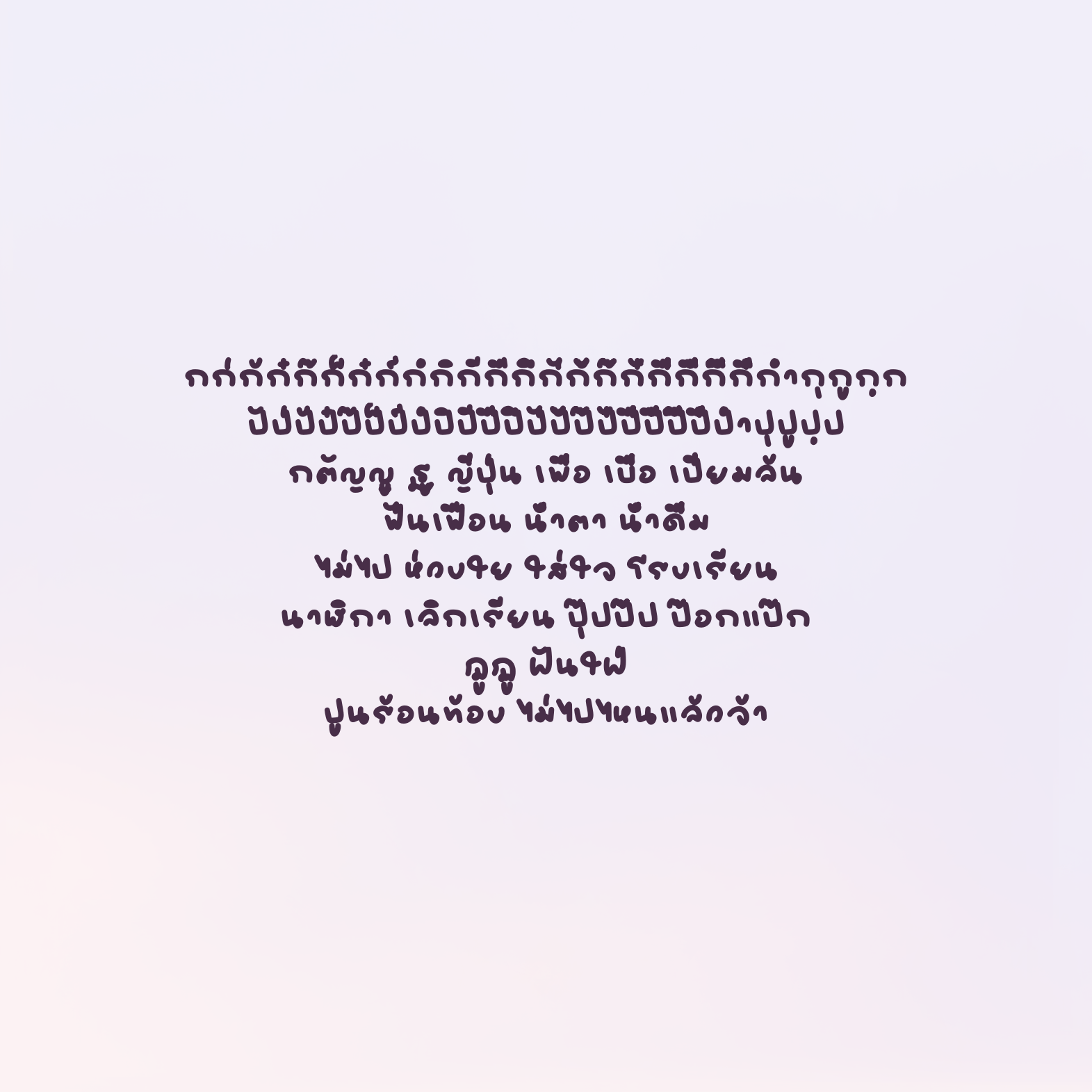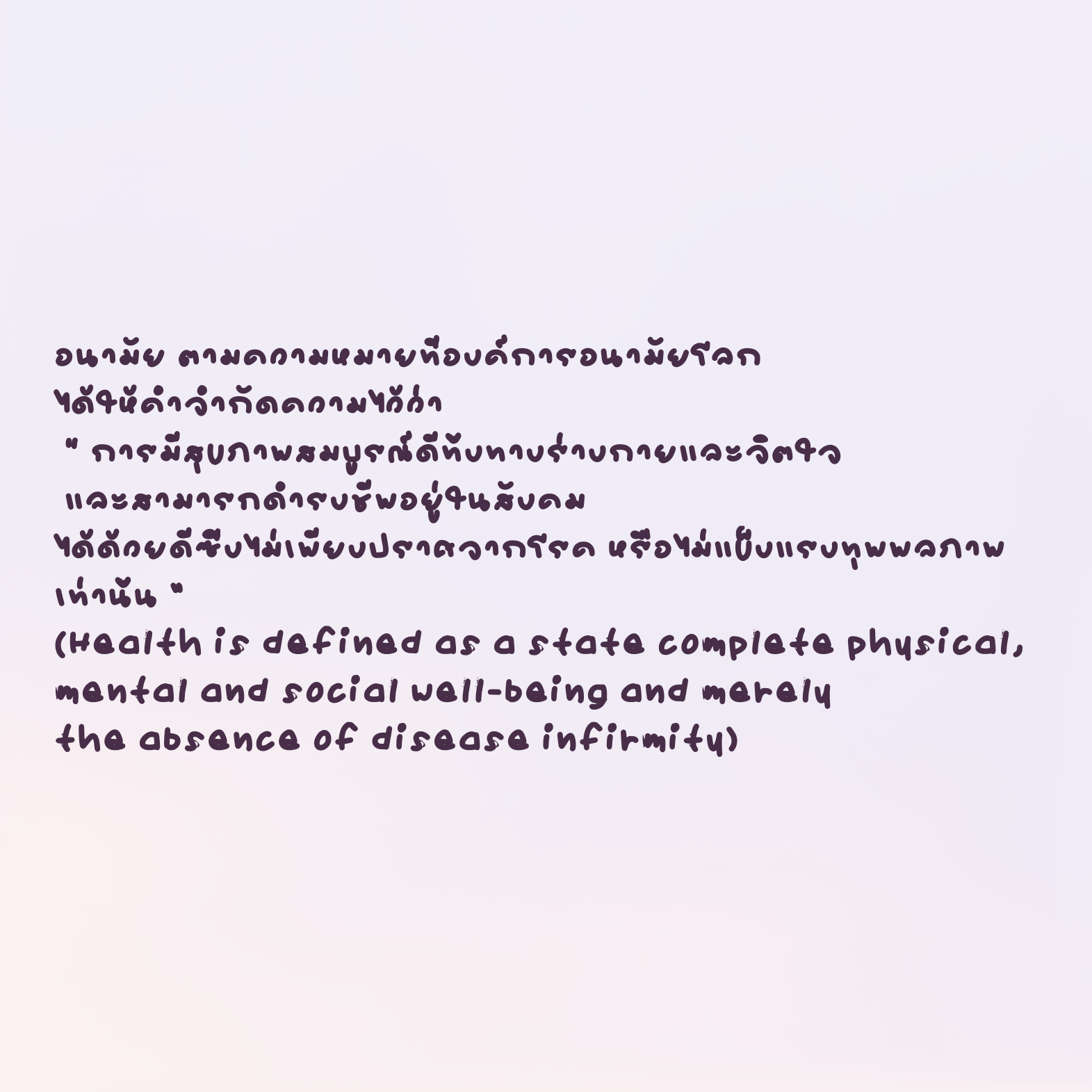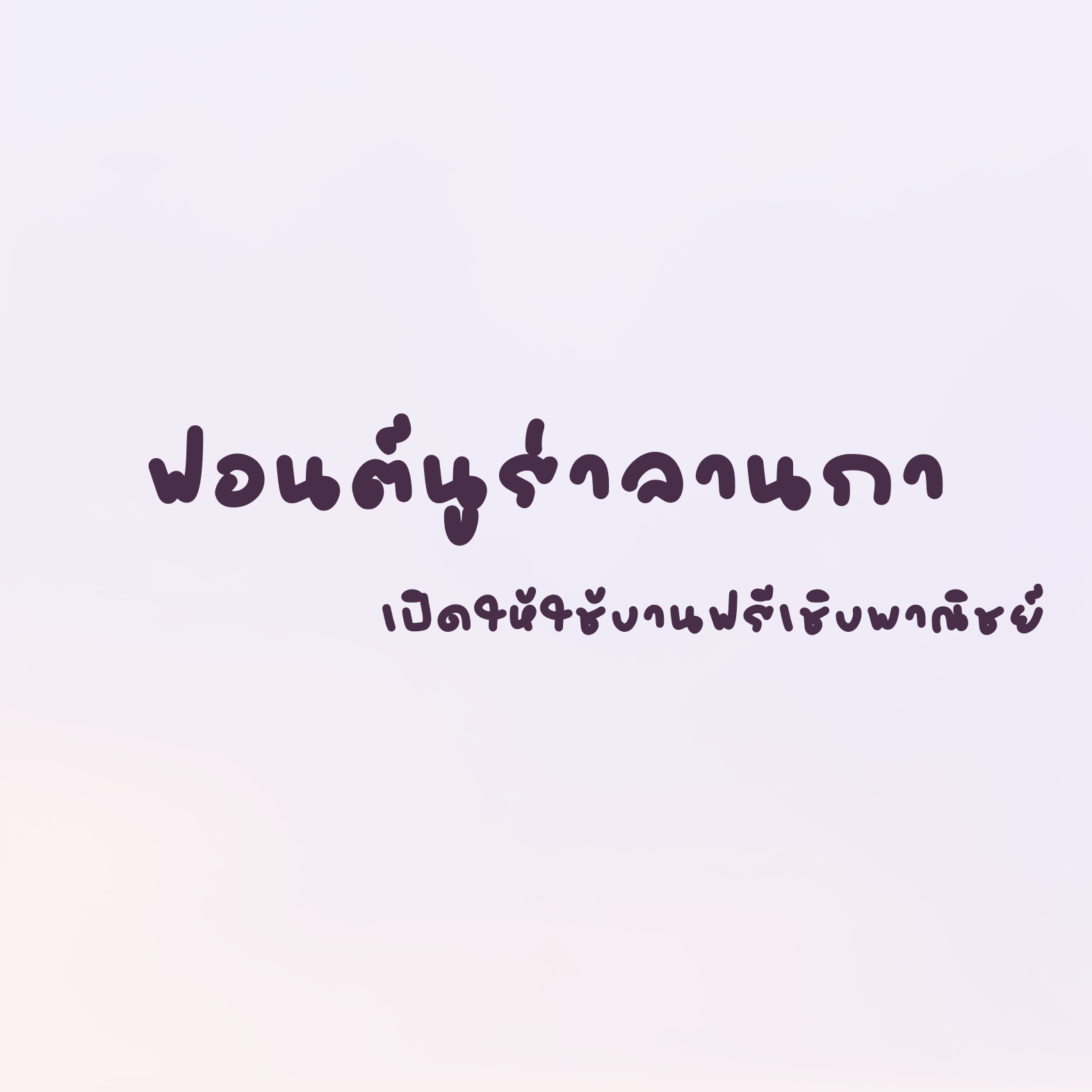
นูร่าลานกา (Nura lanka)
ฟอนต์ลายมือ  ฟอนต์ลายมือไม่มีหัว  มีหนึ่งน้ำหนักคือบาง
แจกให้ใช้งานฟรี สำหรัน้องๆพี่ๆ ที่ชอบฟอนต์ลายมือตัวโยกเยก มีลูกเล่นน่าสนใจ
แนะนำว่า นำไปใช้งานกับการจดเนื้อหา สรุปงาน จดโน๊ต จดบันทึก เป็นลายมือโคตรจะเท่ห์เลย หรือจะนำไปทำคลิป แต่งรูป ก็เริ่ดสุดๆ
อ่านไม่ยาก ถูกใจวัยรุ่น